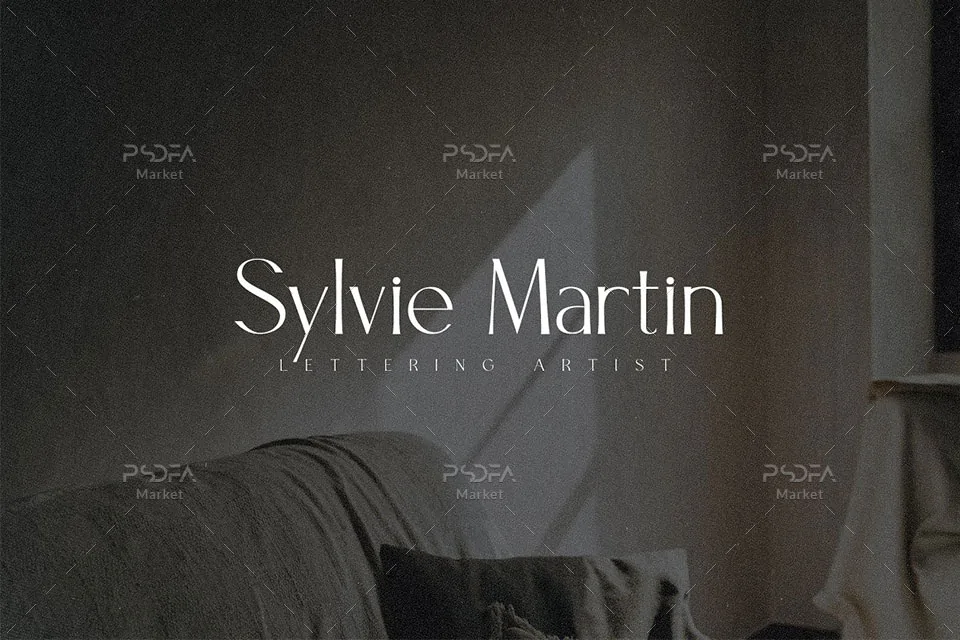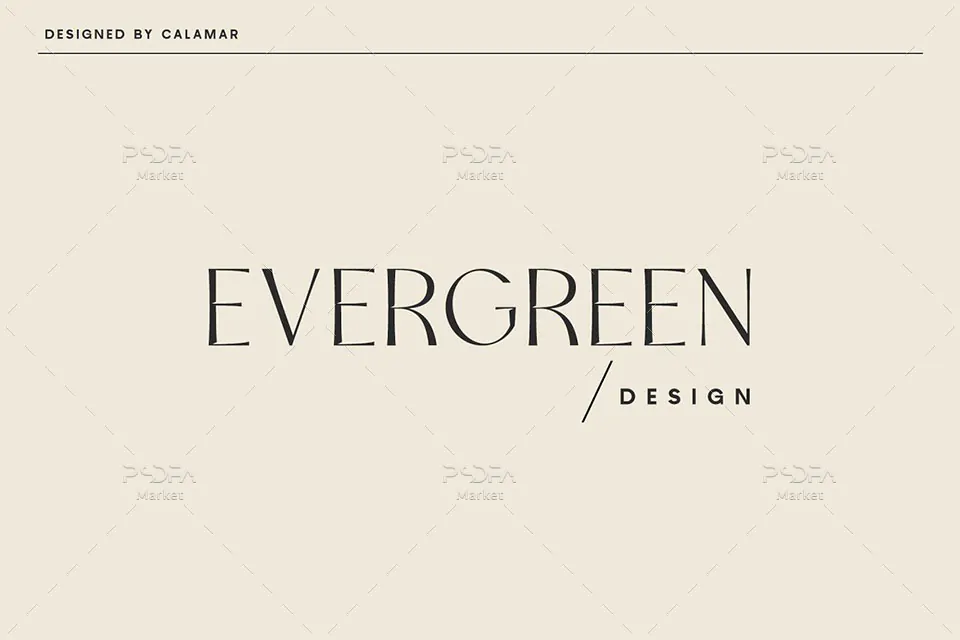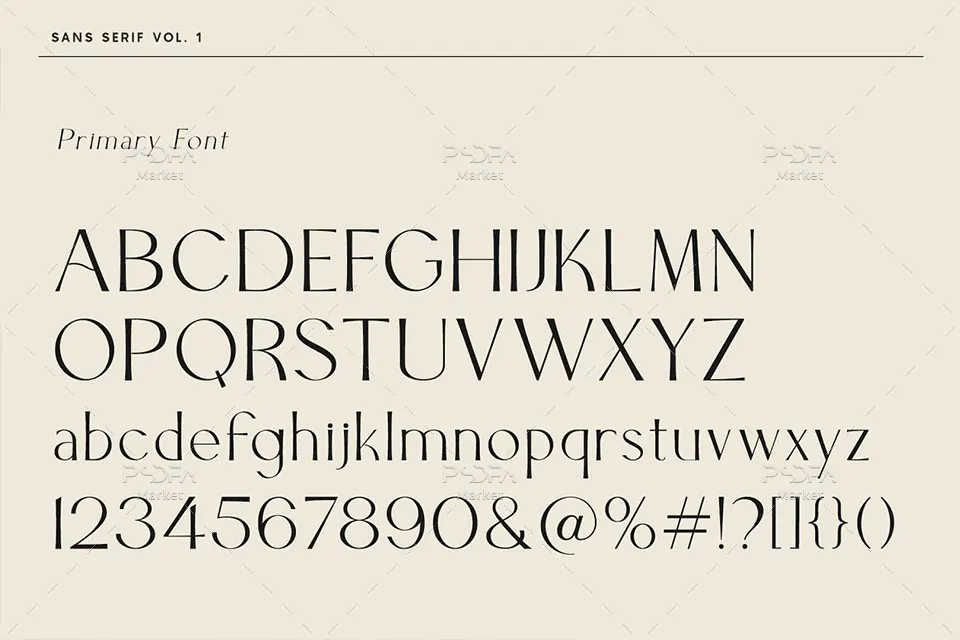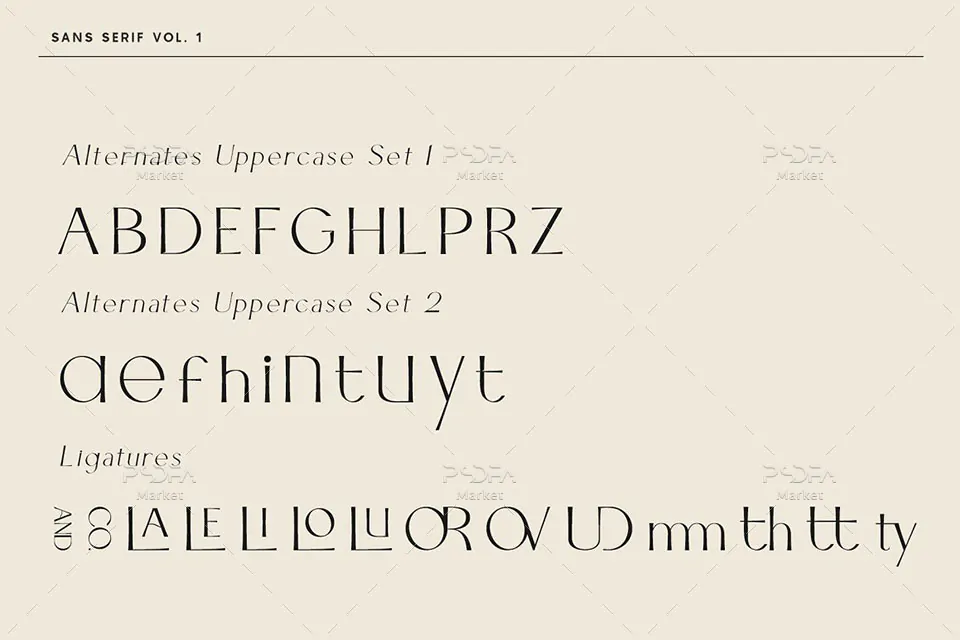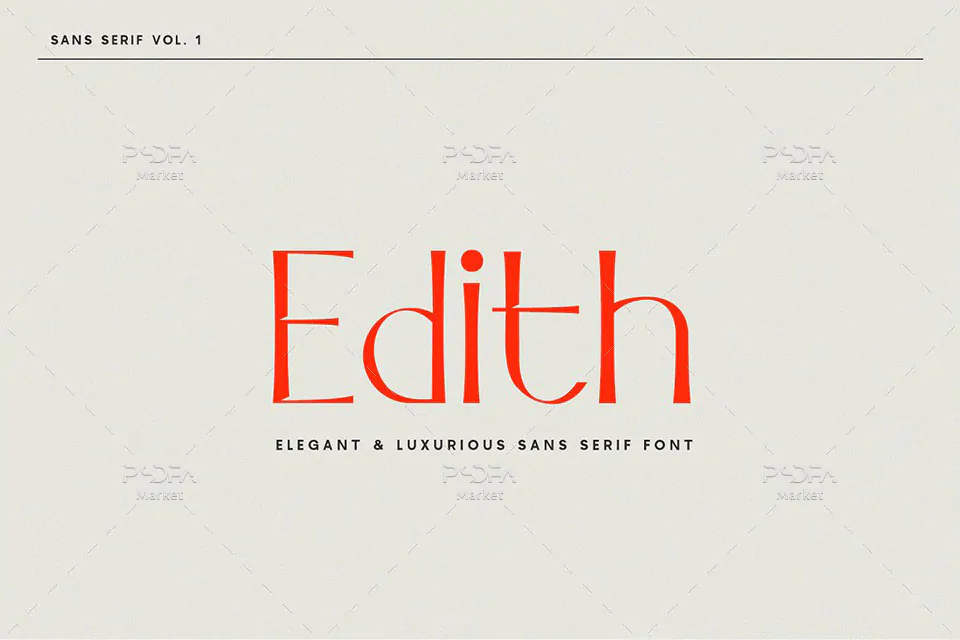
فونت انگلیسی سنس سریف Edith مناسب برای طراحی
فونت انگلیسی سنس سریف Edith
فونت Edith در وزن معمولی (Regular) طراحی شده است که میتوانید از آن در طراحی انواع کارت تبریک، کارت پستال، کارت ویزیت، کارت عروسی، کارت دعوت، طراحی لوگو، کاور آلبوم موزیک، طراحی انواع بنر، پوستر، تراکت، تقویم و دیگر طرحهای گرافیکی استفاده کنید. از نسخه woff این قلم نیز میتوانید در طراحی صفحات وب استفاده کنید.